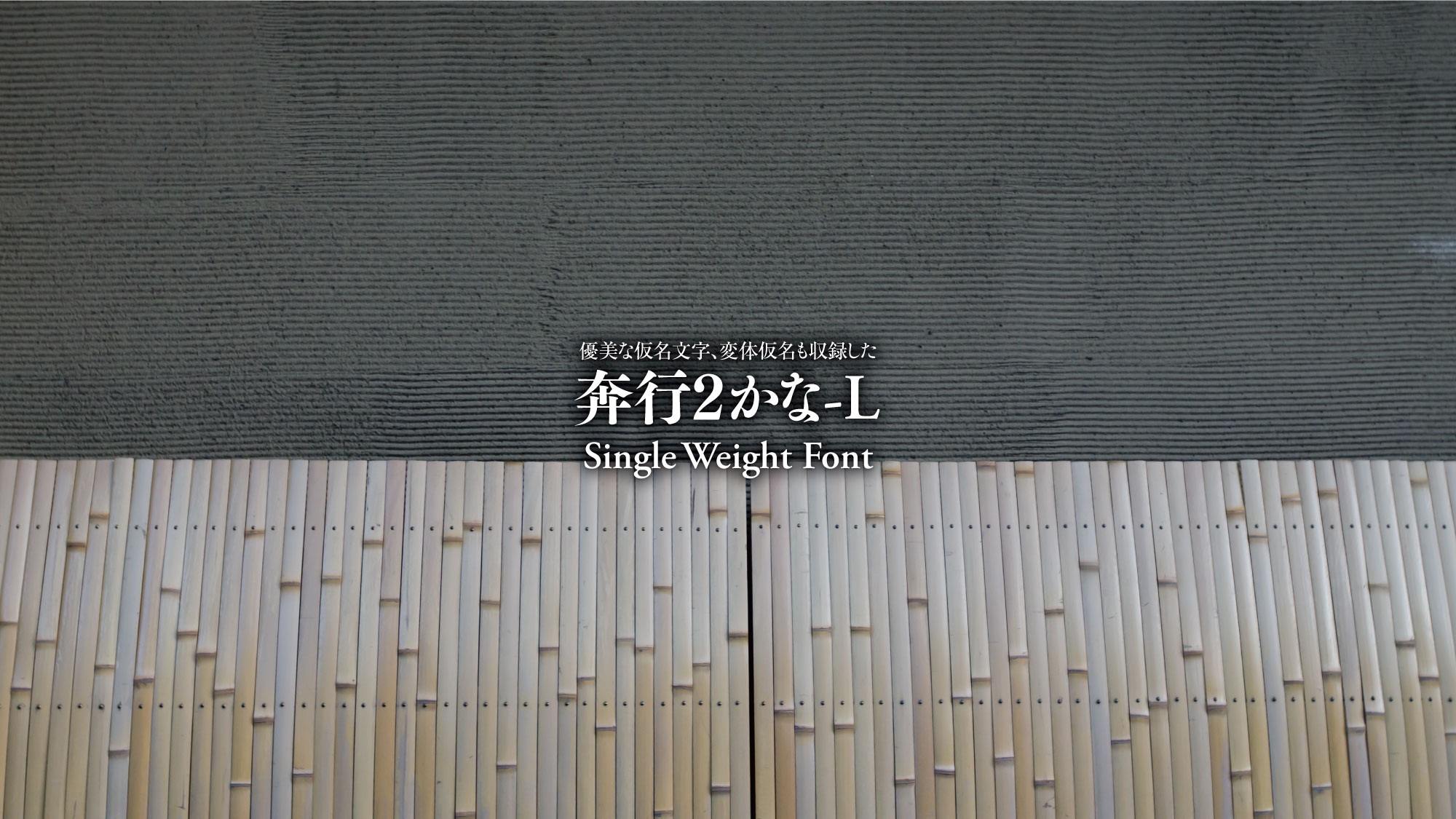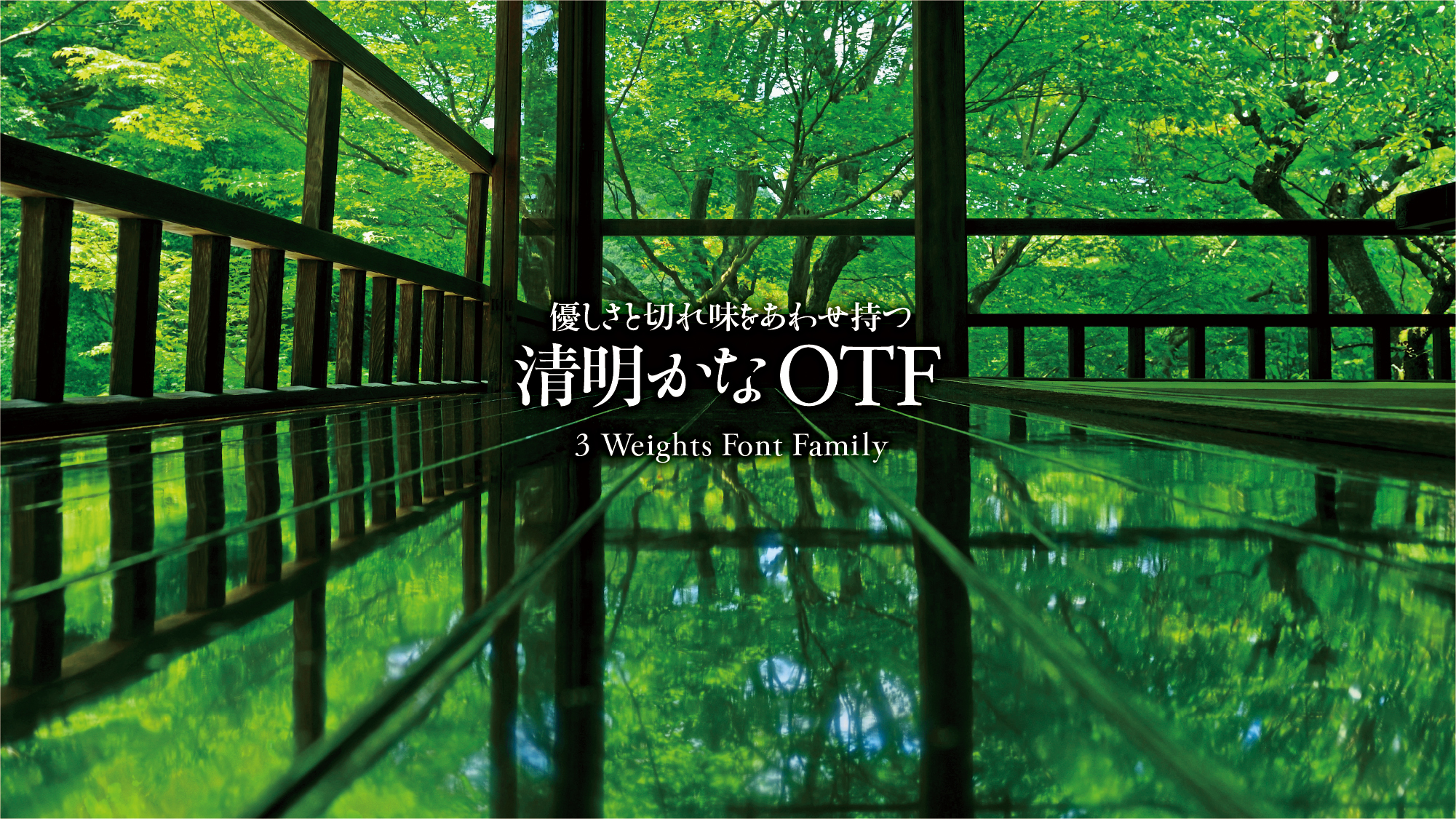
2025.11.21 │ 「日本タイポグラフィ年鑑2026」で入選!
久々21年ぶりに日本タイポグラフィ協会の作品展「年鑑2026」に出品。入選しました。出品作品は、おなじみのフォント、清明かな・余韻かな(タイプデザイン部門)です。
2025.8.25 │ 新欧文フォント「Festoso(フェストーソ)」をリリース!
「ほんまるかな」の従属欧文書体に、欧文フォントとしての機能をプラスして新たに制作しました。名称は「Festoso(フェストーソ)」。音楽用語で「陽気な」「楽しい」といった意味をもちます。
跳ねる文字もあれば、跳ねずにピタッと止まる文字も。予測不能で多様性に富み、リズム感あふれる破天荒な書体です。使っているだけで気分が高まり、無条件に楽しくなってくるようなフォントです。
2025.4.10 │ 本日フォントの日「奔行かなStd-L」後継フォント「奔行2かな-L」をリリース!
2024.12.5 │ コリスさんのブログで、新フォント「清流かな」の特集ページが組まれています!
クリエイティブでタイムリーな情報を常に発信する colissブログ で、新フォント「清流かな」の特集ページを組んでいただきました。大変わかりやすく丁寧に「清流かな」の魅力を発信していただいております。colissブログはこちらから。
2024.12.2 │ 新フォントを「清流かな」リリースしました!